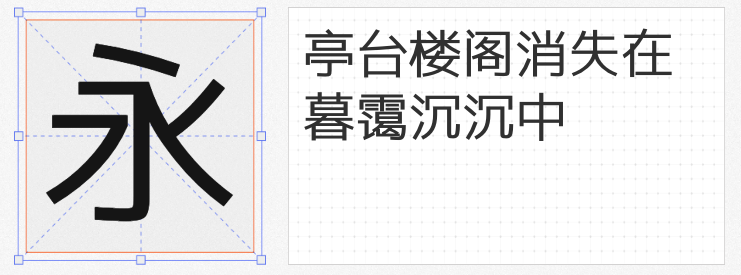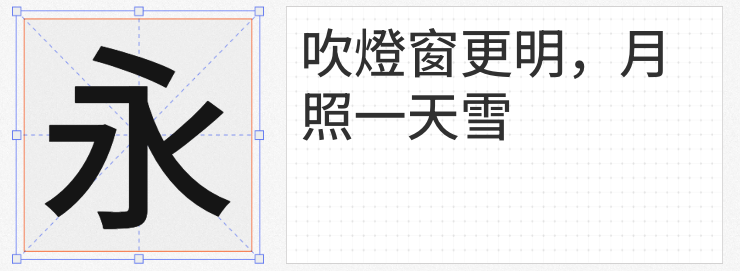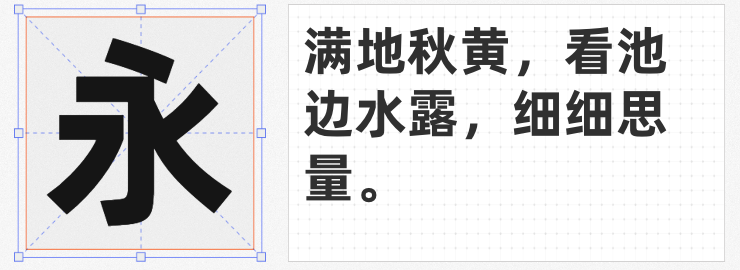
在字体设计的世界里,黑体以其简洁、现代、易读的特点,成为众多设计场景中的优选。无论是海报设计、品牌标识还是网页排版,一款好的黑体都能为作品增添不少分。今天,我们特别推荐四款免费商用的黑体字体,它们不仅设计出众,更能在各种设计需求中展现其独特的魅力。
这款字体专为展现年轻活力而生,中文字体采用现代简洁的笔画设计,造型瘦长且重心提高,完美诠释了20岁阿里巴巴少年的精气神。标题字省略出脚部分,更显简洁大气,无论是标题还是正文,都能轻松驾驭。
作为一款开源字体,思源黑体以其广泛的兼容性和出色的设计赢得了众多设计师的青睐。作为新的开源泛CJK字体家族成员,它不仅支持多种语言环境,更在笔画粗细、结构平衡上做到了极致,是设计中的多面手。
3. 源古黑体
基于思源黑体改造而来,源古黑体在保留思源黑体优秀基因的同时,融入了古籍规范元素,使得字体既现代又不失文化底蕴。其扩B区的字取自遍黑体,经过精心调整,确保了字形的统一与和谐,是古籍风格与现代设计的完美结合。
4. 纳米平汉黑
这款基于M+字体和EmpoSans的黑体补充项目,通过将部分M+字体改为G源,并进行简体补充,实现了常用简体和繁体的全面支持。其设计简洁明了,笔画流畅,无论是印刷还是屏幕显示,都能呈现出清晰易读的效果。
这四款免费商用黑体字体,每一款都拥有其独特的设计理念和适用场景,为设计师们提供了更多元化的选择。